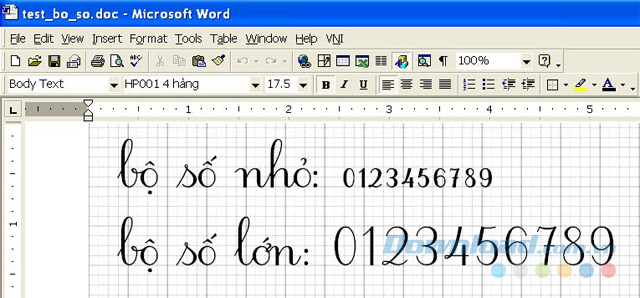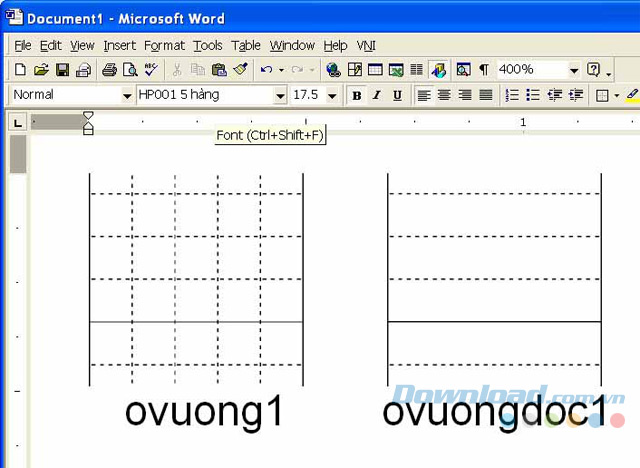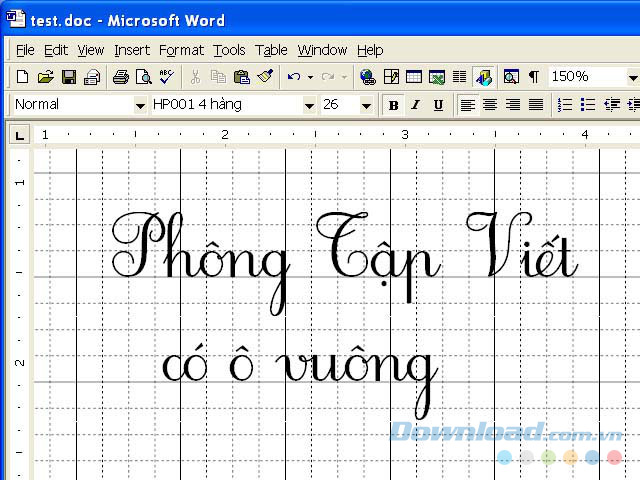
Giới thiệu về Bộ Font Chữ Tập Viết Tiểu Học
Bộ font chữ tập viết tiểu học được thiết kế đặc biệt để hỗ trợ quá trình học tập của trẻ em tiểu học. Khác với các font chữ thông thường, bộ font này chú trọng đến việc thể hiện rõ ràng từng nét chữ, giúp các em dễ dàng nhận biết và bắt chước. Việc luyện viết với font chữ chuẩn sẽ giúp trẻ hình thành thói quen viết chữ đúng, đẹp và ngăn nắp từ khi còn nhỏ, tạo nền tảng tốt cho việc học tập sau này.
Bộ font được xây dựng dựa trên các quy tắc viết chữ chuẩn của Bộ Giáo dục và Đào tạo, đảm bảo tính chính xác và phù hợp với chương trình học. Mỗi nét chữ được thiết kế tỉ mỉ, giúp trẻ dễ dàng phân biệt các nét cong, nét thẳng, nét móc, từ đó hình thành kỹ năng viết chữ chính xác và đẹp mắt. Điều này đặc biệt quan trọng trong giai đoạn trẻ bắt đầu làm quen với việc viết, giúp chúng tránh được những sai sót về kỹ thuật viết, góp phần tạo nên thói quen viết chữ đẹp ngay từ đầu.
Tính năng nổi bật của bộ font:
- Đạt chuẩn Bộ Giáo dục và Đào tạo: Bộ font tuân thủ nghiêm ngặt các quy định về chữ viết của Bộ Giáo dục và Đào tạo, đảm bảo tính chính xác và phù hợp với chương trình giảng dạy.
- Thiết kế rõ ràng, dễ nhìn: Từng nét chữ được thiết kế rõ ràng, dễ nhìn, giúp trẻ dễ dàng nhận biết và bắt chước. Sự rõ ràng này không chỉ hỗ trợ trẻ trong việc luyện viết mà còn giảm thiểu sự mệt mỏi cho mắt khi tập trung vào bài viết.
- Hai loại font: 4 hàng và 5 hàng: Bộ font cung cấp hai lựa chọn: font 4 hàng (giống tập học sinh 4 ô ly) và font 5 hàng, giúp người dùng linh hoạt lựa chọn tùy theo nhu cầu sử dụng. Sự đa dạng này cho phép người dùng lựa chọn loại font phù hợp với từng loại bài tập và sở thích của trẻ.
- Hỗ trợ tạo ô ly: Bộ font cho phép người dùng tạo ra các ô ly trên văn bản bằng cách thêm các mã đặc biệt, giúp mô phỏng hoàn hảo quyển tập học sinh. Tính năng này mang đến sự thuận tiện, giúp người dùng tạo ra các bài tập viết có ô ly một cách nhanh chóng và dễ dàng.
- Ứng dụng đa dạng: Bộ font không chỉ phục vụ cho việc luyện viết chữ của học sinh tiểu học mà còn có thể được sử dụng bởi giáo viên trong công tác giảng dạy, tạo ra các tài liệu học tập chất lượng cao. Việc sử dụng font chữ chuẩn trong việc soạn giáo án hay tài liệu giảng dạy sẽ giúp nâng cao chất lượng bài giảng và tạo nên sự thống nhất về mặt chữ viết.
Bộ font chữ tập viết tiểu học là một công cụ hỗ trợ đắc lực cho việc luyện viết chữ đẹp của trẻ em tiểu học. Với thiết kế chuẩn xác, dễ sử dụng và nhiều tính năng hữu ích, bộ font này sẽ giúp các em nhỏ hình thành thói quen viết chữ đúng, đẹp và rèn luyện kỹ năng viết hiệu quả. Sự kết hợp giữa việc sử dụng bộ font này và sự hướng dẫn tận tình của phụ huynh, giáo viên sẽ góp phần tạo nên nền tảng vững chắc cho việc học tập và phát triển của trẻ trong tương lai. Hy vọng những thông tin trên sẽ giúp các bạn hiểu rõ hơn về bộ font và cách sử dụng nó hiệu quả.